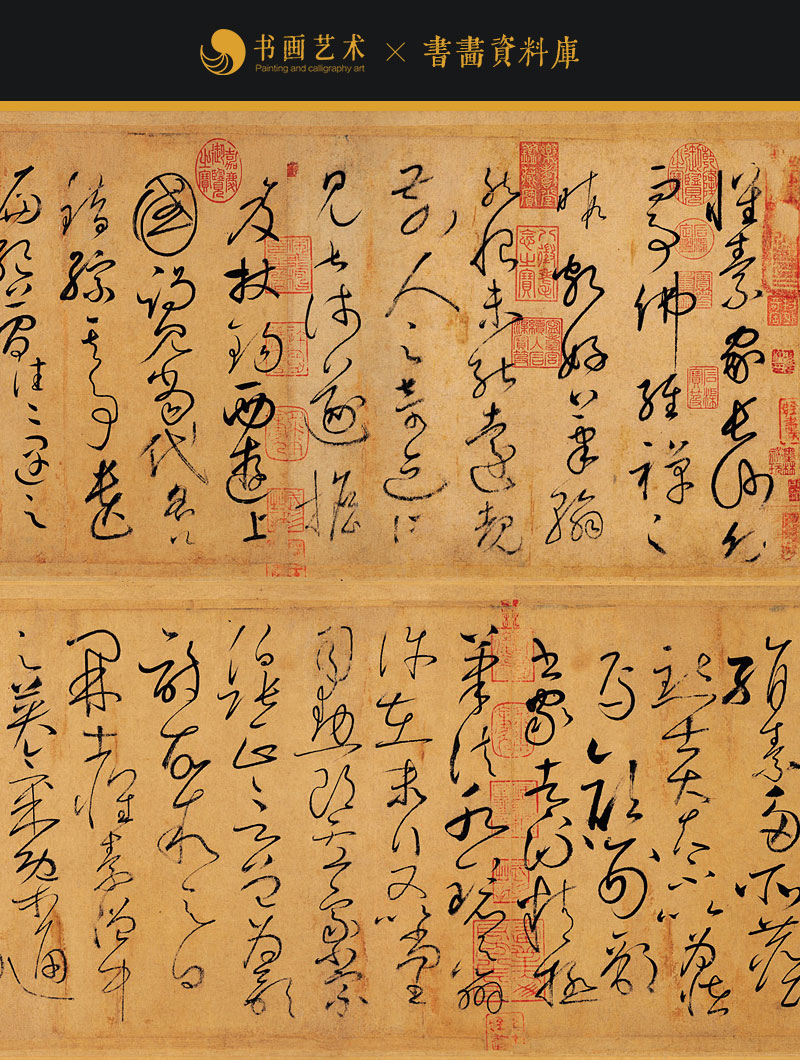
《自叙帖》是唐代书法家怀素于唐大历十一年或十二年(776或777年)创作的草书书法作品,为纸本墨迹卷。现收藏于台北故宫博物院。《自叙帖》为怀素自述其生平大略,兼录颜真卿、张谓、戴叔伦等人对其的赠诗成文。通篇为狂草,笔笔中锋,如锥划沙盘,纵横斜直,无往不收;全卷强调连绵草势,运笔上下翻转,忽左忽右,起伏摆荡,有疾有速,有轻有重,通幅于规矩法度中,奇踪变化,神采动荡,实为草书艺术的极致表现。